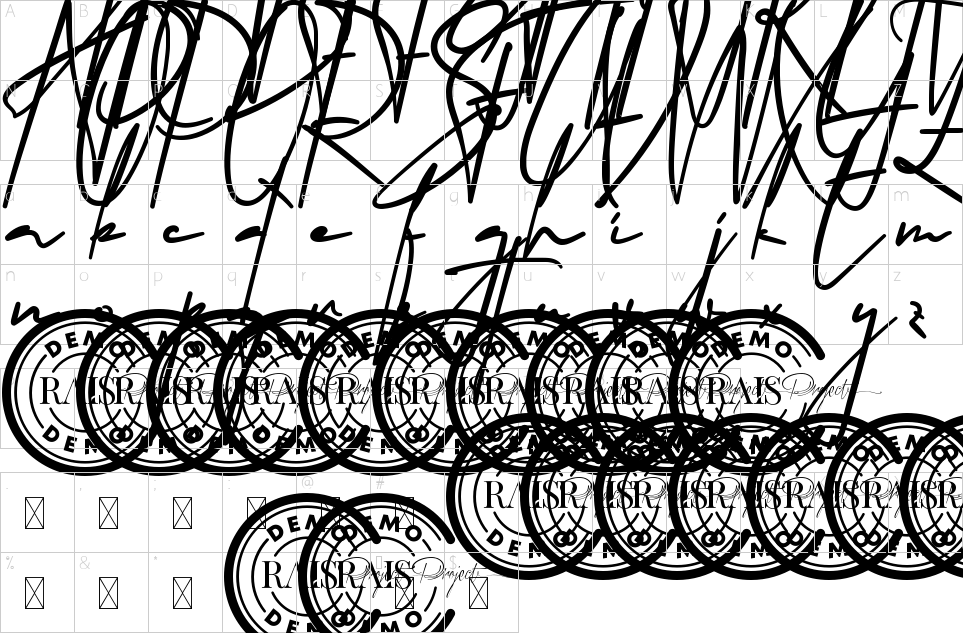
A fonte Musical Theater é uma opção gratuita e envolvente para os criadores de arte digital e designers de gráficos. Ela foi criada por RaisProject e já foi baixada 1.505 vezes. Ideal para ilustrações de teatro, esse tipo de fonte é perfeito para aqueles que gostam de adicionar um toque de teatro em suas criações digitais. Seja em uma página de site, um arquivo de PowerPoint ou qualquer outro projeto de design digital, essa fonte irá deixá-lo destacar sua mensagem com um touch especial. Com uma aparência elegante e um design cuidadosamente elaborado, a Musical Theater é a escolha perfeita para quem quer dar um toque de personalização e originalidade em seus projetos.